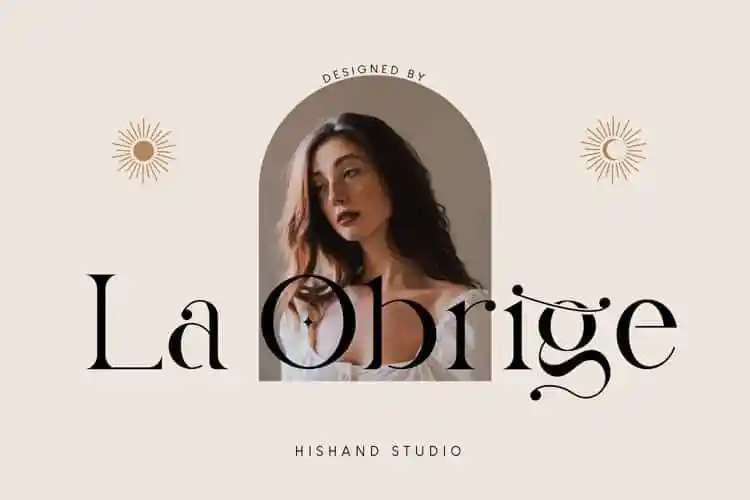
La Obrige Serif Font
La Obrige Serif é uma elegante tipografia serif que trará um estilo único e tendência aos seus designs. Inspirada na Parisidade e no encanto francês, esta fonte foi criada pela Hishand Studio para quem busca um toque sofisticado em seus projetos gráficos. Suas linhas elegantes são ideais para logotipos de marca, marcas, posts nas redes sociais, embalagens de produtos e publicidade, oferecendo uma presença visual impecável que destaca seu conteúdo. Adote La Obrige Serif para adicionar um toque atraente e sofisticado aos seus materiais gráficos. Ideal tanto para iniciantes quanto para profissionais, essa fonte será certamente sua nova preferência quando estiver buscando uma tipografia de qualidade que se destaca do resto da concorrência.